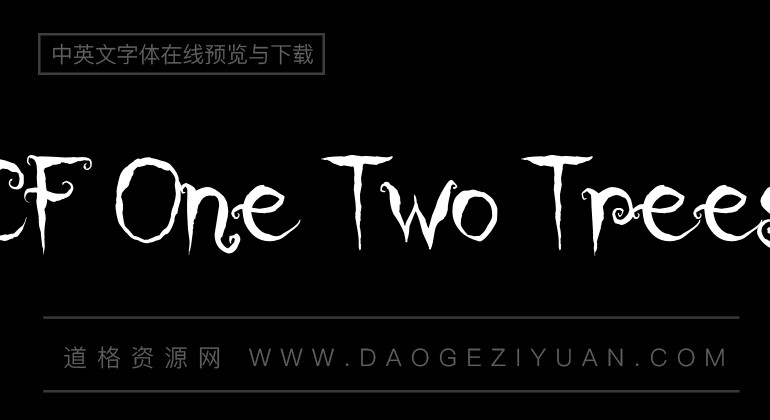
CF One Two Trees
CF One Two Trees 是一款由字体设计师 CloutierFontes 所设计的字体,其设计灵感来自于大自然中的树木。 这个字体的特点是线条圆润、柔和,许多字母中带有弯曲的线条,可以让整个字体看起来更加生动、自然。这款字体的字母大小也比较一致,字母之间的间隔也比较均匀,整体呈现出一种简洁、舒适的感觉。 CF One Two Trees 可以用于多种设计场合,例如海报、标志、包装、漫画等。这个字体还有多种字重可以选择,从 Light 到 Bold 都有,用户可以根据需要选择不同的字重来达到不同的效果。 总之,CF One Two Trees 是一款非常有特色的字体,它的设计元素来自自然界中的树木,给人以亲切、温暖的感觉,非常适合用于那些需要表现自然、亲近的设计场合。
CF One Two Trees是一款非常不错的手写艺术字体,具有很好的视觉感,适合于文化类的宣传设计、商业类品牌的广告和产品包装设计以及个性化文字排版等较多场景。